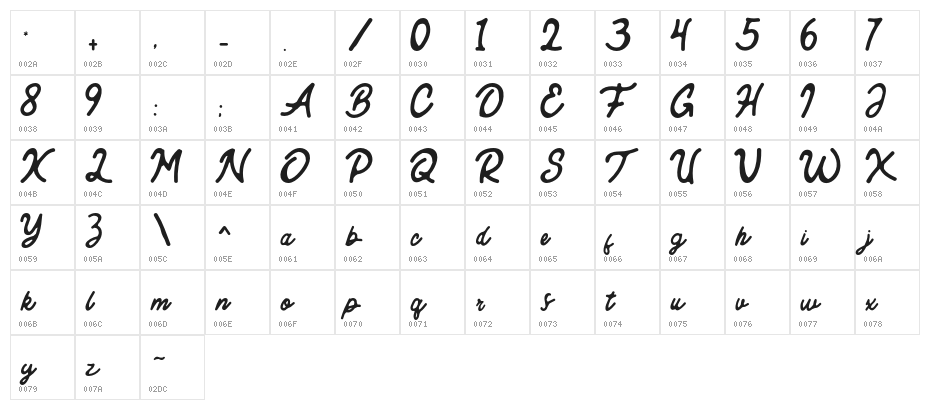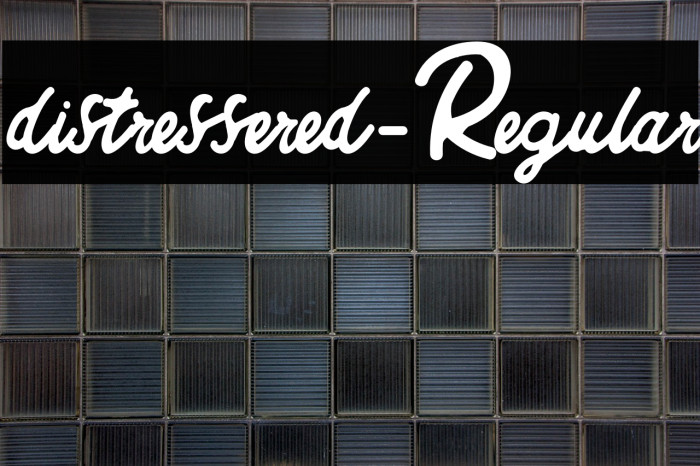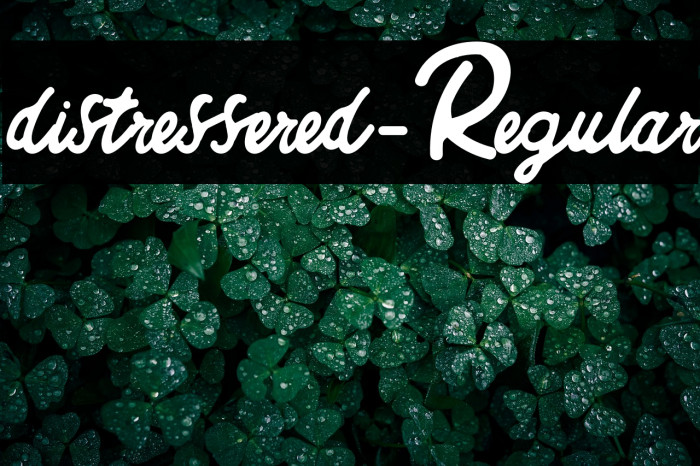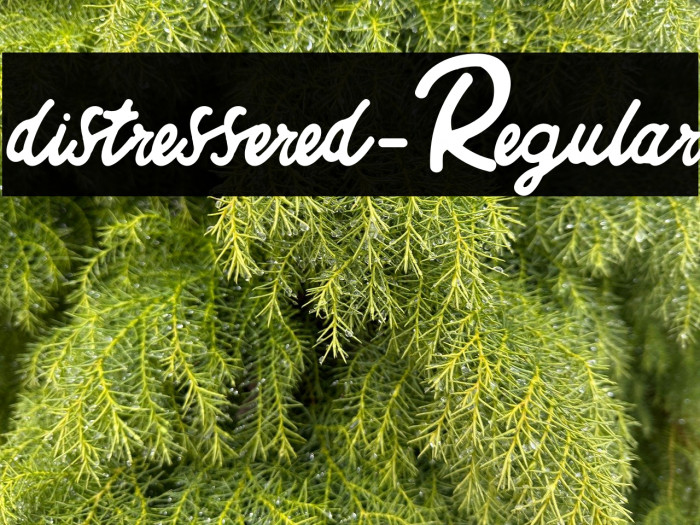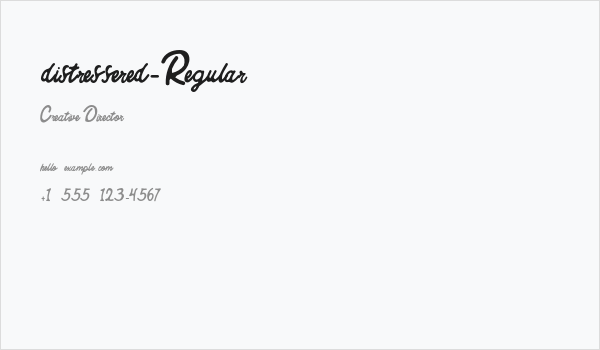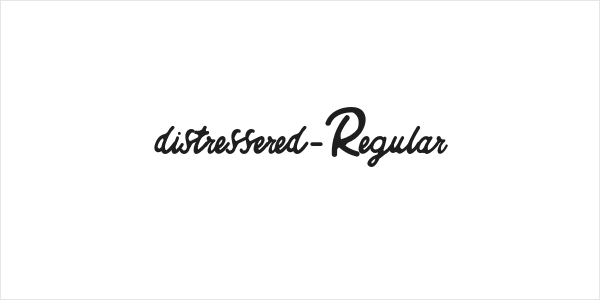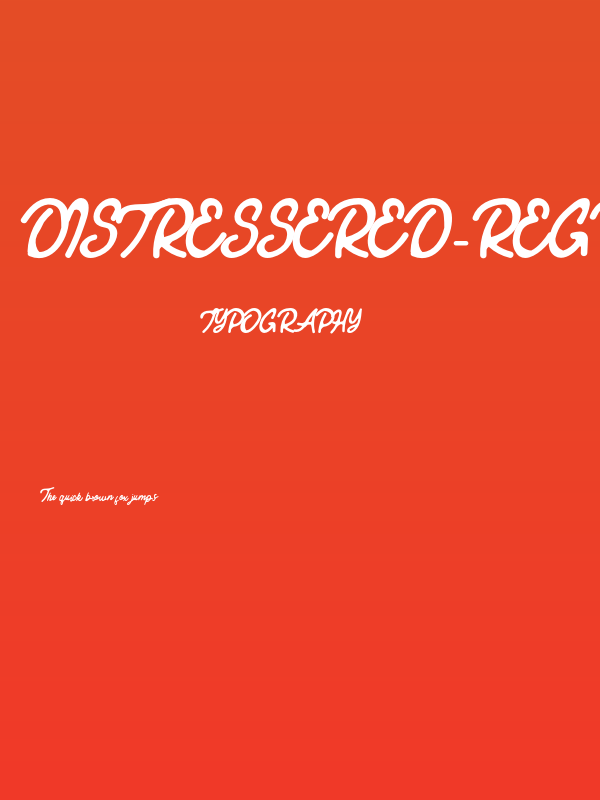
distressered-Regular Font
| 整体风格 | Vintage |
| 使用场景 | Logos, Headlines, Posters |
| 推荐项目 | Ideal for vintage-themed posters, logos, and branding materials that require a handcrafted, nostalgic feel. |